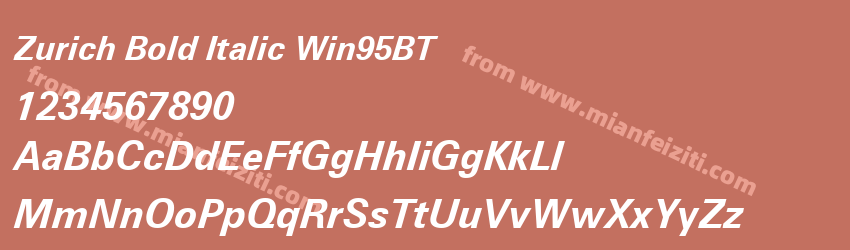
Zurich Bold Italic Win95BT
字体名称: Zurich Bold Italic Win95BT
Postscript名称: ZurichBT-BoldItalic
本款“Zurich Bold Italic Win95BT”是一款书写很新颖的字体,字体大方,适合各种设计作品使用!欢迎下载!